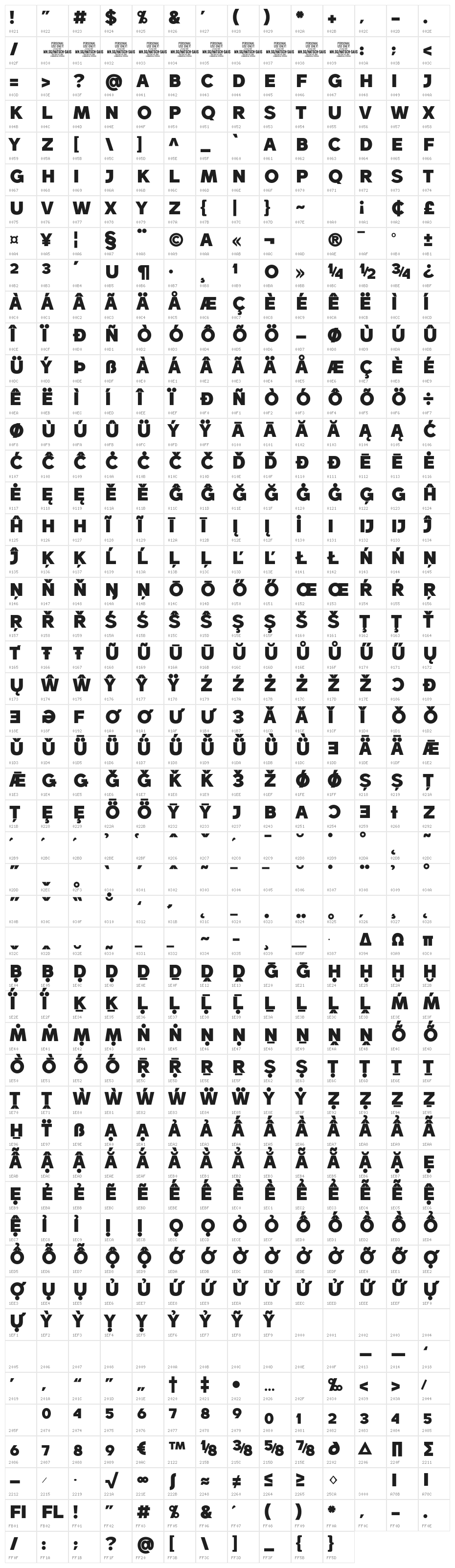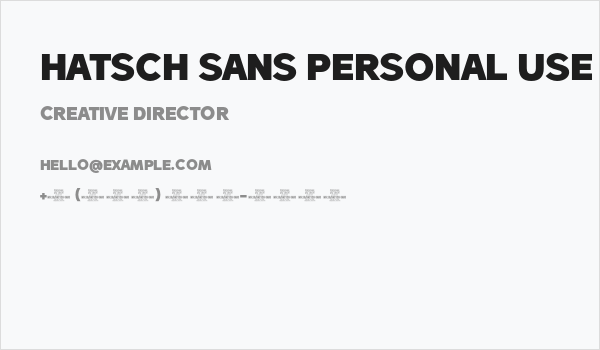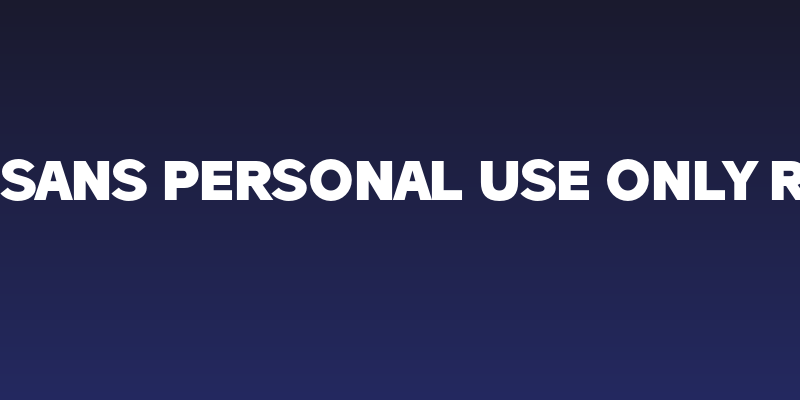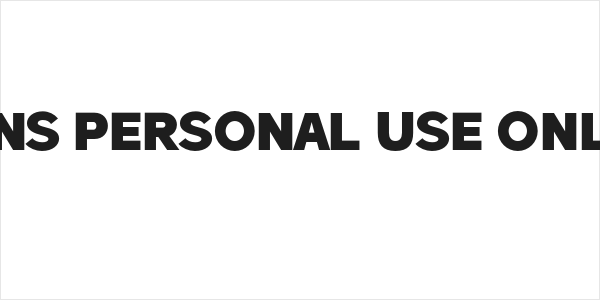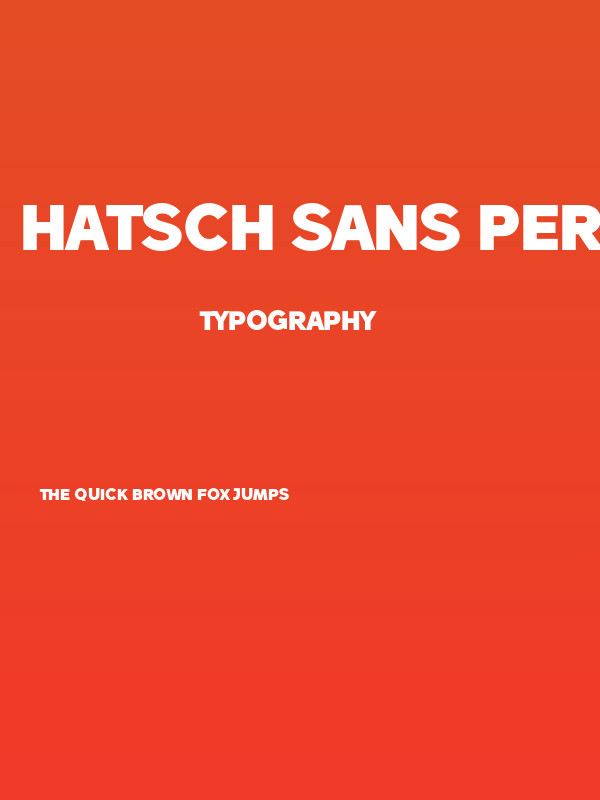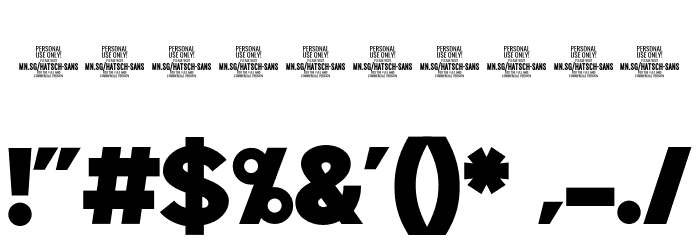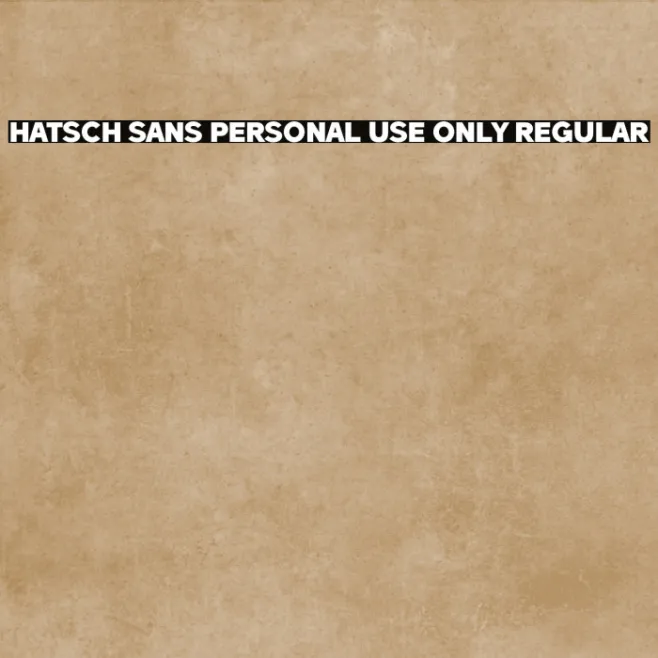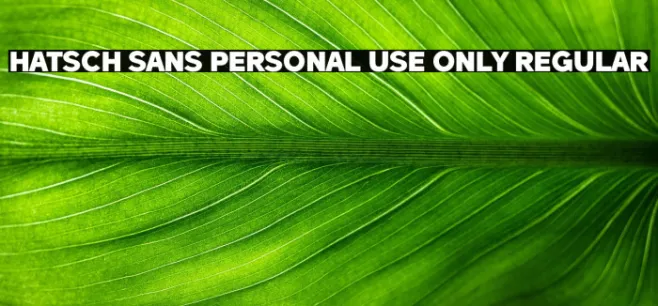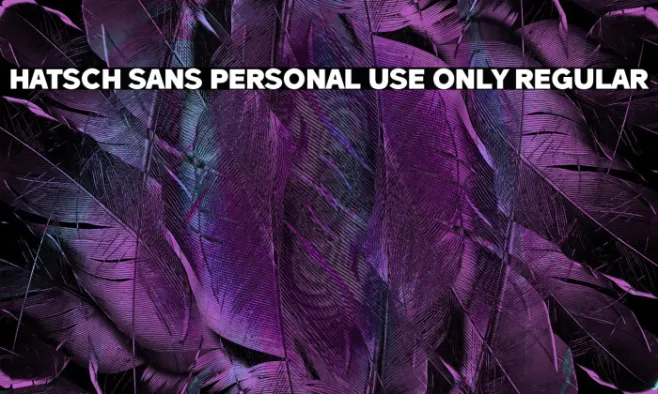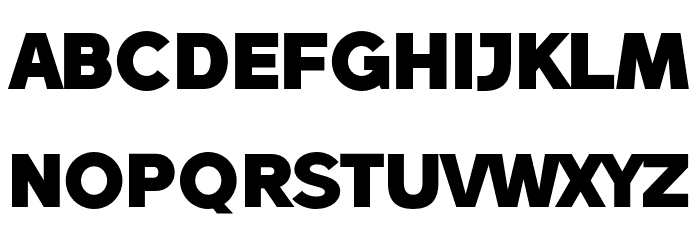
Hatsch Sans PERSONAL USE ONLY Regular Font
| Name | Hatsch Sans PERSONAL USE ONLY Regular |
| Schriften Familie | Hatsch Sans PERSONAL USE ONLY |
| Kategorien | Sans Serif |
| Breite | Expanded |
| Vorgeschlagene Projekte | Ideal for branding, headlines, posters, and advertising where a strong, modern impact is needed. |